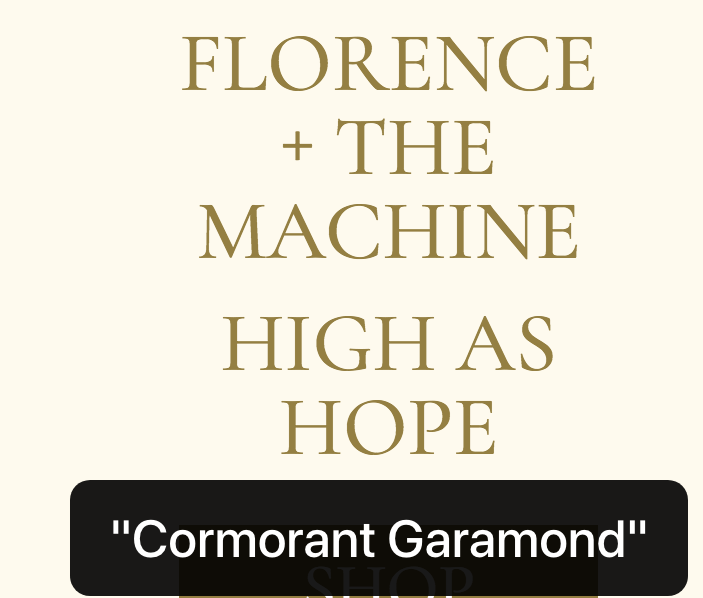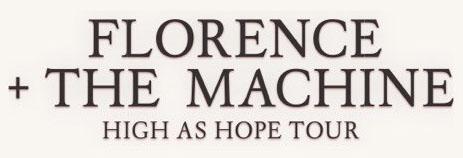
Schrift Artwork Florence + the Machine
Auf der von dir verlinkten Seite verwenden sie einen Google-Font:
Die gesuchte ist ebenfalls eine Garamond. Welche genau, weiß ich nicht. Die "Elegant Garamond" kommt von der Serifenform ganz gut hin, aber das R ist abweichend …